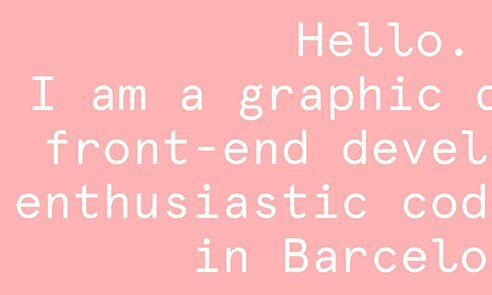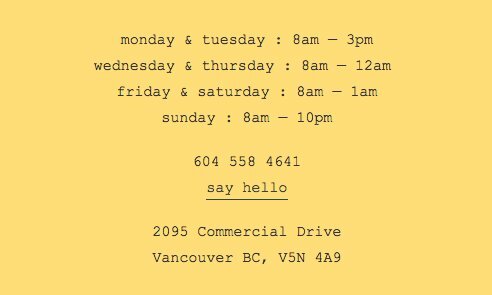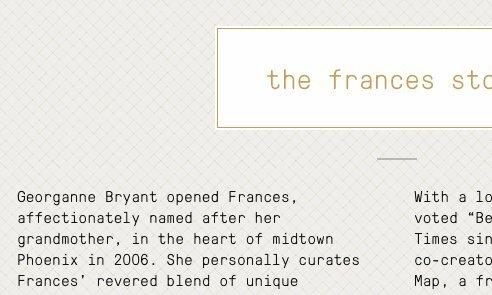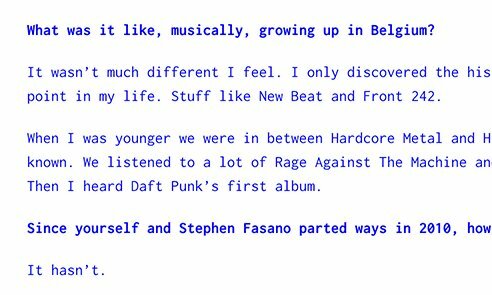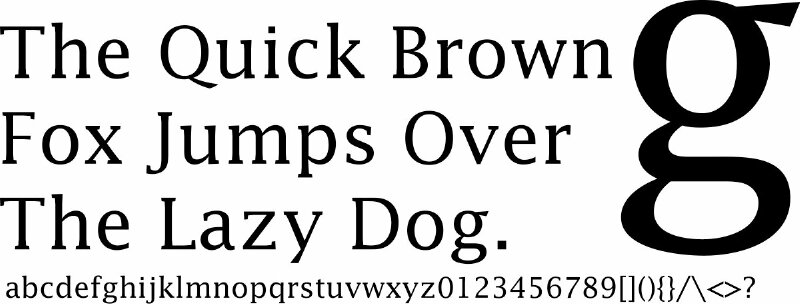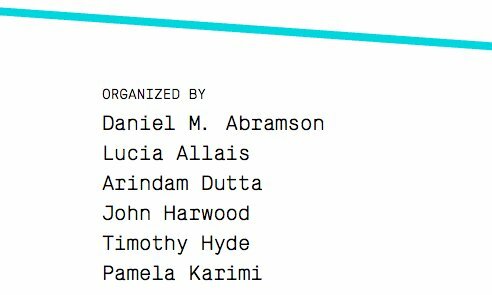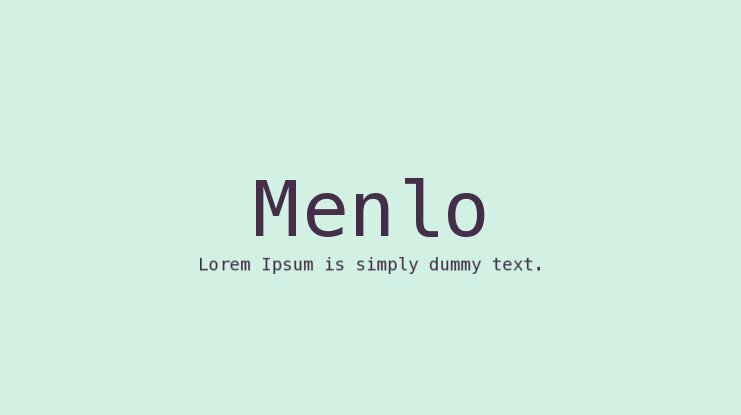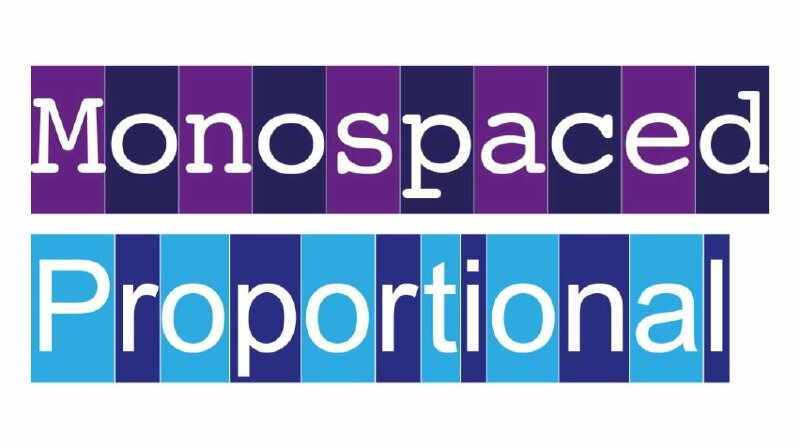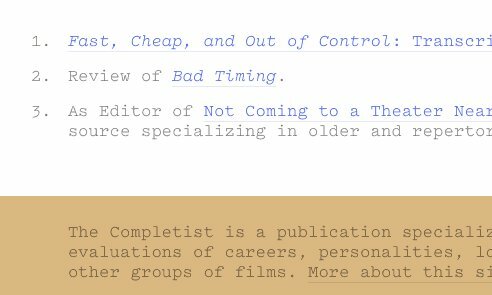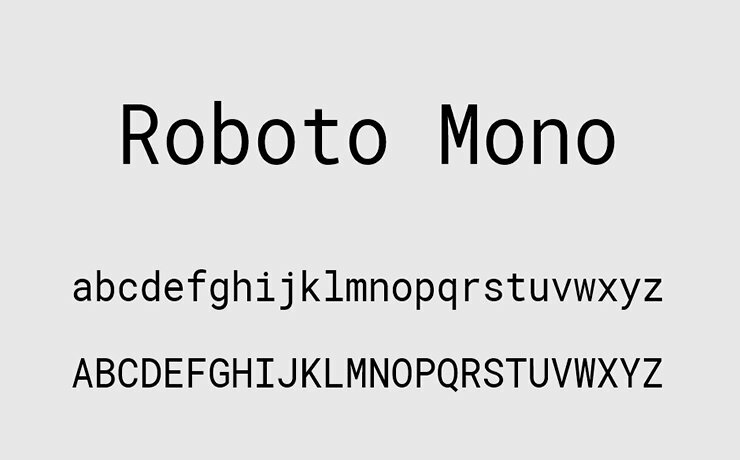
Monospace font là gì? Đặc điểm và ứng dụng của font chữ monospace
Monospace font là gì? Tìm hiểu các điểm và ứng dụng của font chữ monospace. Các Typeface thuộc nhóm Monospace được sử dụng phổ biến nhất hiện nay
Monospace font là gì?
Monospace font (Phông chữ đơn cách) là font chữ trong đó mỗi ký tự đều có cùng chiều rộng (cùng một khoảng cách theo chiều ngang. Điều này có nghĩa là các ký tự trong phông chữ monospace đều chiếm một khoảng không gian ngang như nhau, dù kích thước thực tế của ký tự có lớn hay nhỏ.
Monospace font là gì?
Phông chữ Monospace được phát minh từ thời đánh máy để đáp ứng các yêu cầu cơ học của máy đánh chữ, được ứng dụng hàng đầu trong việc soạn code hoặc tạo hiệu ứng cổ điển mô phỏng máy đánh chữ,..
Đặc điểm và ứng dụng của font chữ monospace
Phông chữ monospace có đặc điểm và ứng dụng như sau:
Đặc điểm và ứng dụng của font chữ monospace
• Monospace là loại phông chữ có đặc điểm các ký tự có cùng kích thước và khoảng cách, tạo nên sự nhất quán trong văn bản.
• Monospace thường được áp dụng rộng rãi trong lĩnh vực lập trình để hiển thị mã nguồn và dữ liệu. Nó tạo nên một giao diện rõ ràng và trực quan, đặc biệt phù hợp cho các mục đích kỹ thuật.
• Monospace font thường được sử dụng trong các ứng dụng liên quan đến mã nguồn, trình biên dịch, bảng giá cổ phiếu, bảng biểu, và các dạng văn bản mà yêu cầu sự cân đối chính xác giữa các ký tự và các cột dữ liệu,.. vì rõ ràng, dễ dàng đọc và hiểu.
Các Typeface thuộc nhóm Monospace được sử dụng phổ biến nhất hiện nay
Sau đây là các Typeface thuộc nhóm Monospace được sử dụng phổ biến nhất hiện nay.
Font Courier
Courier là một trong những phông chữ monospace truyền thống nhất, được biết đến với các serifs đơn giản. Nó có kiểu dáng truyền thống với các serif nhỏ và đường viền sắc nét. Courier được tạo ra bởi IBM vào những năm 1950 và đã trở thành một trong những phông chữ được sử dụng rộng rãi trong việc hiển thị mã lệnh và văn bản đồng đều.
Font chữ Lucida
Lucida là một font chữ Monospace được phát triển bởi nhà thiết kế Charles Bigelow và Kris Holmes vào những năm 1980 và đến nay đã có nhiều phiên bản khác nhau. Lucida là một font chữ linh hoạt và được sử dụng rộng rãi trong các ứng dụng kỹ thuật và thiết kế đồ họa.
Font chữ Menlo
Menlo là một font chữ Monospace phát triển bởi Apple. Nó có kiểu dáng hiện đại, sắc nét và dễ đọc. Menlo có các ký tự rõ ràng và đồng nhất, giúp tạo ra một giao diện mã nguồn dễ theo dõi và căn chỉnh chính xác.
Font chữ Space Mono
Space Mono là một phông chữ monospace hiện đại, nổi bật với các góc cạnh và đường nét sắc nét. Space Mono được phát triển bởi Colophon Foundry, Space Mono mang đến một sự kết hợp giữa kiểu dáng retro và hiện đại.
Font chữ GT Pressura Mono
GT Pressura Mono là một phông chữ monospace có thiết kế độc đáo và gần gũi với phông chữ bằng tay. GT Pressura Mono được phát triển bởi Grilli Type, một nhà thiết kế font chữ nổi tiếng. Nó là một phiên bản Mono của GT Pressura, một font chữ sans-serif. GT Pressura Mono thường được sử dụng trong thiết kế đồ họa, in ấn, trình biên dịch và các ứng dụng liên quan đến lập trình.
Font chữ Pitch
Pitch là một font chữ Monospace với kiểu dáng đơn giản và đồng nhất. Đây là một font chữ Monospace cổ điển và phổ biến trong ngành in ấn và máy đánh chữ từ những năm 1800.
Font chữ Inconsolata
Inconsolata là một font chữ Monospace với kiểu dáng sáng tạo và dễ đọc, được phát triển bởi Raph Levien và là một trong những font chữ Monospace phổ biến trong cộng đồng lập trình. Inconsolata có các đường viền sắc nét và các chi tiết độc đáo như đỉnh cong trên một số ký tự, tạo nên một cái nhìn độc đáo và thân thiện.
Font chữ Maison Mono
Maison Mono là một phông chữ monospace mang đến sự hài hòa giữa cổ điển và hiện đại. Maison Mono được tạo ra bởi phòng thiết kế "Milieu Grotesque", có thiết kế độc đáo, với các chi tiết tinh tế và sự cân đối hoàn hảo. Điều này tạo ra một sự pha trộn giữa sự cổ điển và sự hiện đại.
Font chữ Apercu Mono
Apercu Mono là một font chữ Monospace, một font sans-serif được phát triển bởi nhà thiết kế Colophon Foundry, các ký tự có khoảng cách rộng. Apercu Mono có kiểu dáng đơn giản và trực quan, với các đường viền sắc nét và các chi tiết tinh tế. Nó mang đến một cái nhìn hiện đại và thanh lịch.
Font chữ Roboto Mono
Roboto Mono là một phông chữ Monospace được phát triển bởi Google. Nó là một trong những font chữ phổ biến và tiêu chuẩn trên nền tảng Android. Roboto Mono có kiểu dáng đơn giản và rõ ràng, với các đường viền sắc nét và sự cân đối chính xác của các ký tự. Nó mang lại một cái nhìn hiện đại và dễ đọc.